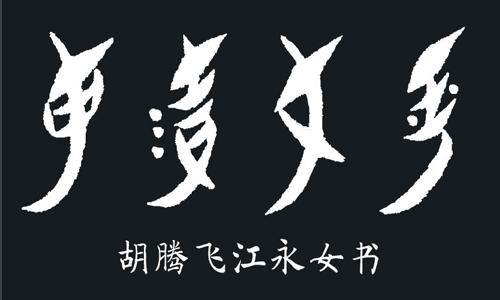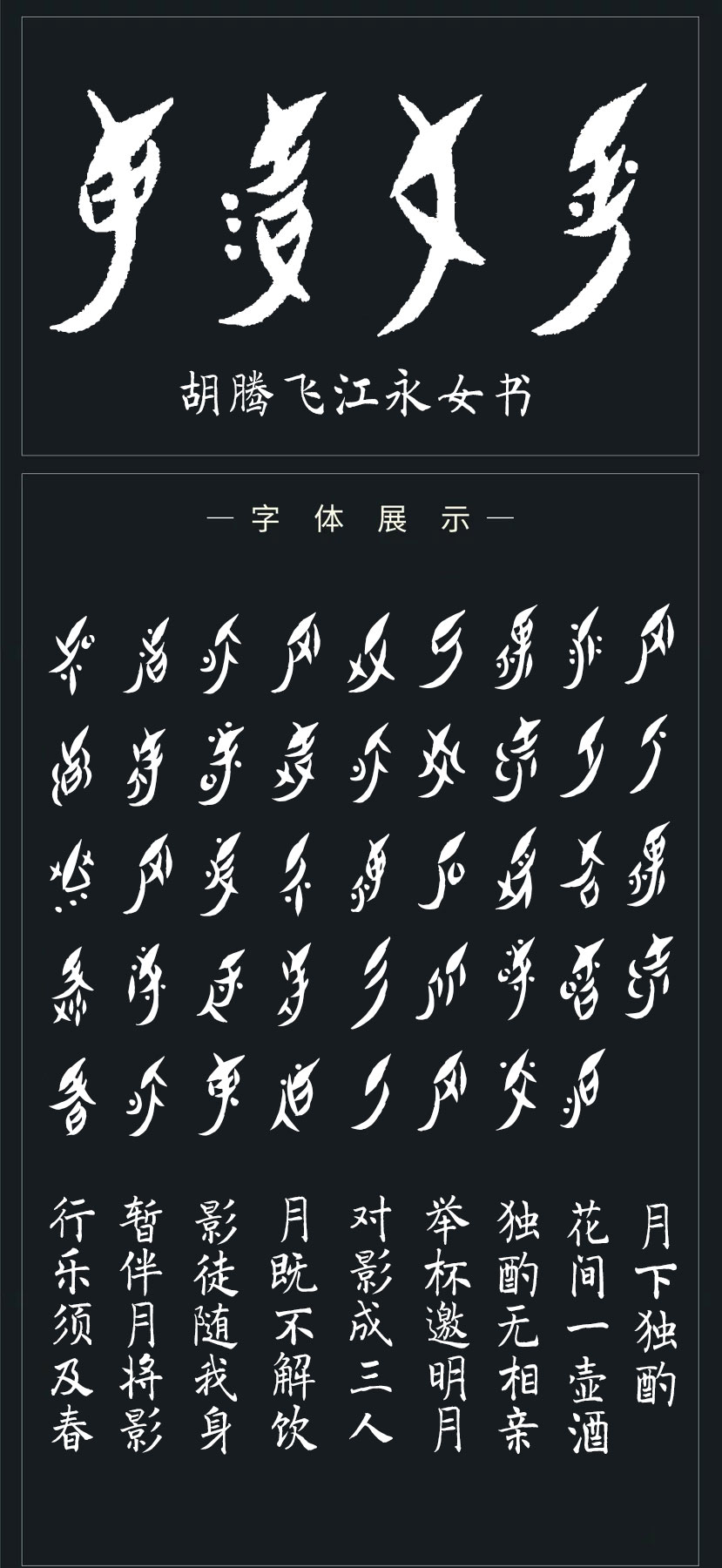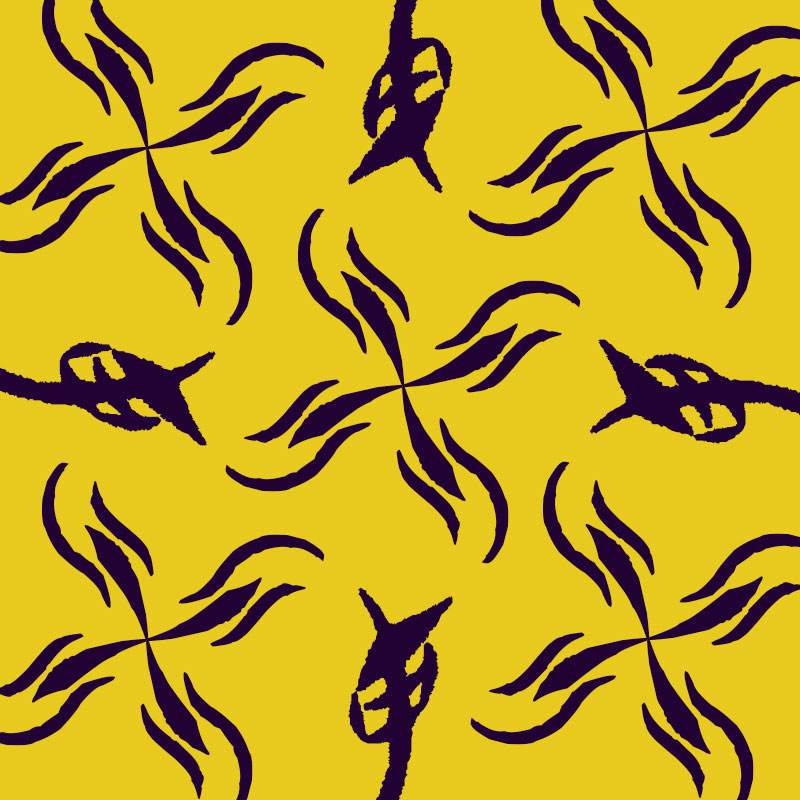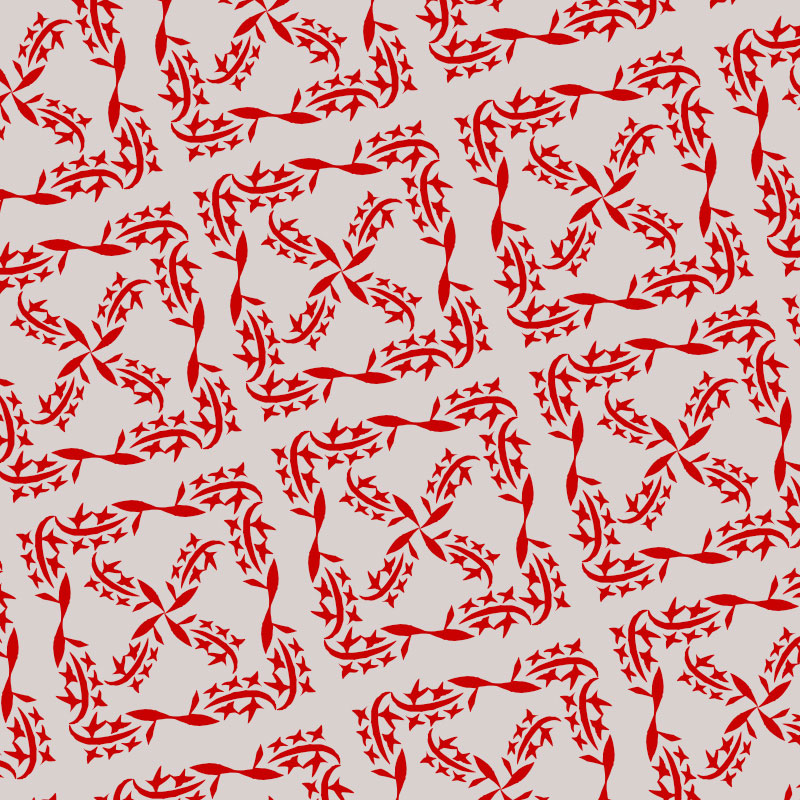
胡騰飛江永女書字體是世界上唯一存在的女性文字,呈長菱形,筆畫纖細(xì)均勻。隨著時(shí)代的發(fā)展,現(xiàn)在女書只是在湖南江永縣一些農(nóng)村老年婦女中使用,女書面臨著瀕臨滅絕的境地。做這套字的初衷很簡單,發(fā)現(xiàn)網(wǎng)上還沒有一套完整的女書字庫,就想盡一點(diǎn)自己的微薄之力,做了這套江永女書字庫,讓大家更好的了解女書。歡迎喜歡胡騰飛江永女書字體的朋友前來下載使用。
字體展示
女書花布藝術(shù)圖案
上圖女書文字為-江水
上圖女書文字為-鼠